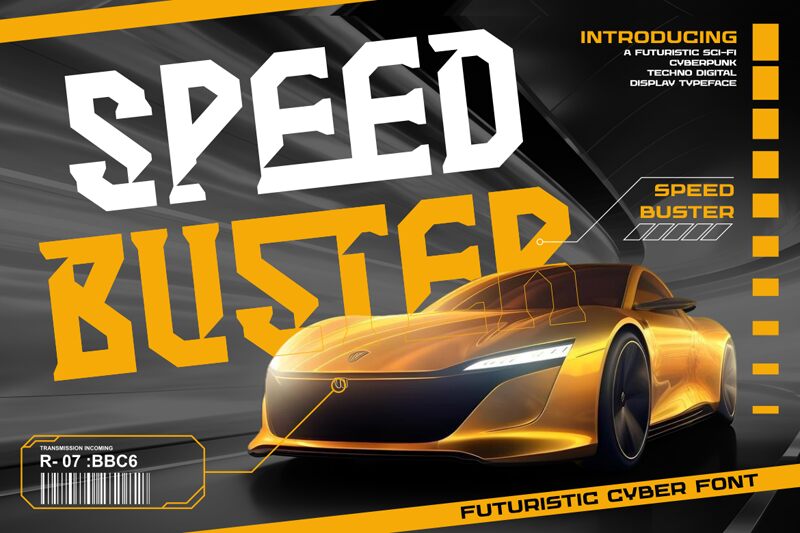
Speed Buster de Shanaf Studio es una tipografía display de estilo techno gratuita con un marcado toque blackletter. Sus letras parecen talladas en bloques sólidos, mezclando formas medievales quebradas con un ritmo digital rígido. Las diagonales repetidas, las esquinas recortadas y las verticales pesadas le dan a la fuente un pulso rápido, muy de estilo gaming.
Esta mezcla es perfecta para branding de e-sports, flyers de música, gráficos de streetwear, títulos de pósters y miniaturas de YouTube, donde una fuente gratuita necesita más garra que una sans-serif de ciencia ficción convencional. También funciona de maravilla en títulos cortos y logotipos, ya que su textura compacta e entrelazada hace que incluso unas pocas letras se sientan densas y llenas de energía.